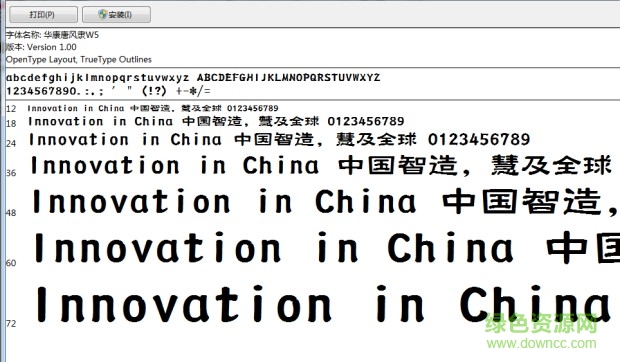
軟件介紹 軟件標簽: 華康唐風隸 華康字體 字體 華康唐風隸W5字體是一款華康字體庫中的個性字體,該字體可以適用于名片設計、平面設計、廣告設計、報紙雜志、企業(yè)LOGO、商標注冊、電視臺廣告等領域,有喜歡的網(wǎng)友可免費下載收藏。字體安裝方法方法一:控制面板/字體/文件/安裝新字體;方法二:直接將字體復制到C:\WINDOWS\Fonts。方法三:針對win7系統(tǒng),用戶只需選中字體右鍵安裝即可。注意事項本站所有字體資源僅供個人學習與參考,如需商業(yè)使用請到相關官網(wǎng)授權。 軟件截圖 上一張下一張(1 / 1) 安裝詳細截圖 其他版本下載 標題 大小 更新日期 下載 下載地址 電腦版 華康唐風隸w5 p 點擊報錯 軟件無法下載或下載后無法使用,請點擊報錯,謝謝! 關閉報錯反饋 請描述您所遇到的錯誤,我們將盡快予以修正,謝謝! *必填項,請輸入內容 本類最新 華康漆隸體繁w5 wow魔獸世界華康少女字體ttf 免費版 華康蕓風體w3 繁體 華康pop2體w9 p 華康粗黑體繁 dfpyuanw7字體 ttf版 相關文章 Photoshop字體安裝使用方法和技巧 如何解決“無法新增字體”問題 Win 7系統(tǒng)安裝字體方法 網(wǎng)頁字體大小設置方法 怎么改網(wǎng)頁字體大小 在Linux系統(tǒng)中安裝字體的幾種方法 windows7字體顯示問題:打開某些程序的時候顯示的是亂碼 用戶評論 熱門評論 最新評論 發(fā)表評論 查看所有評論(0) 昵稱: 請不要評論無意義或臟話,我們所有評論會有人工審核. 字數(shù): 0/500 (您的評論需要經(jīng)過審核才能顯示)